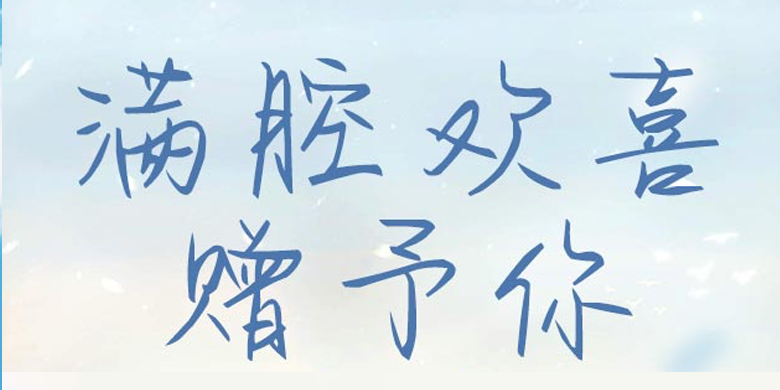
方正手迹-满腔欢喜赠予你
方正手迹-满腔欢喜赠予你,这款字体结构工整、笔画清晰,兼顾美观与易读性,适用于标题、正文、海报、包装、LOGO 等多种场景。字形优雅稳定,风格百搭耐看,适配日常排版与创意设计,让文字呈现更舒适、更具质感。方正手迹-满腔欢喜赠予你一笔一画,皆是细节,以均衡的比例、流畅的线条打造舒适视觉体验,字形端正大气,风格简约现代。无论是商业设计、品牌宣传还是日常排版,都能轻松驾驭,让文字更有格调与力量。方正手迹-满腔欢喜赠予你字体下载。
满腔欢喜赠予你,这款字体线条锐利果敢,轻重对比明显,字形放荡不羁,自由随性,亦如少年心性热情似火,满腔欢喜。适用于文艺类的书刊、品牌广告和产品包装设计,影视用字,以及社交网络的个性化用字。